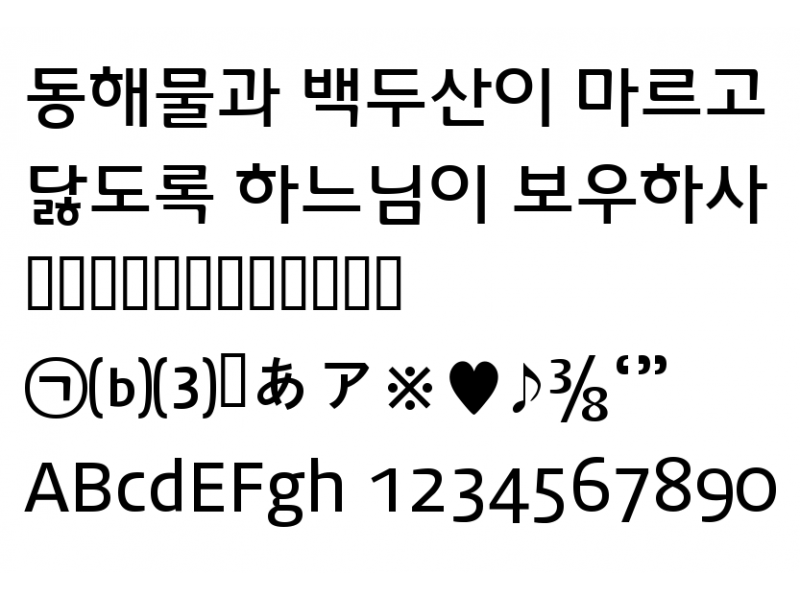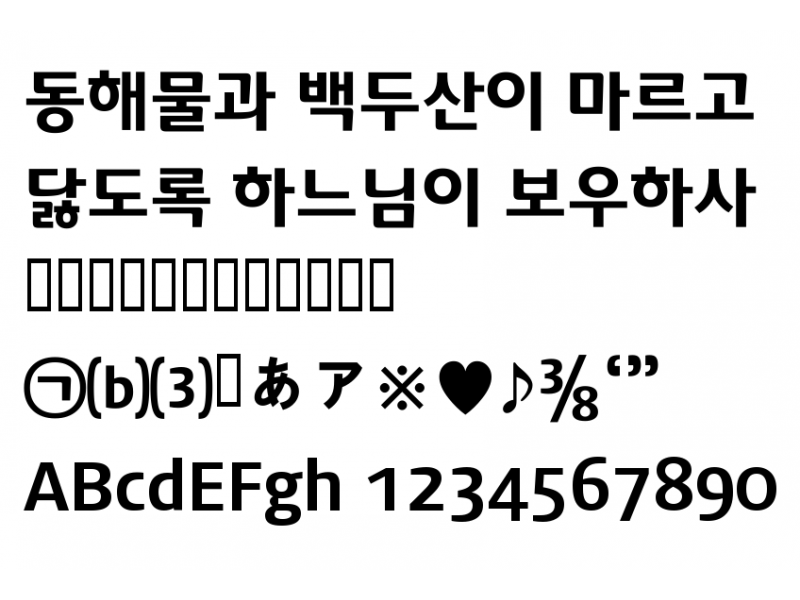
다음체는 다음커뮤니케이션이 2008년 9월 17일 공개한 완성형 2350자 제목형 서체이다.
'Daum Regular.ttf' 와 'Daum SemiBold.ttf' 2종으로 구성되어 있다. 폰트 디자인은 좋은글씨가 한글 서체에 참여했으며, 영문 서체는 네덜란드 디자인회사 토털아이덴티티가 담당하였다. 상업적인 목적으로 사용할 수 없다. 2015년경 공식 배포가 중단되었으나, 현재 네이버자료실에서는 다운로드할 수 있다.